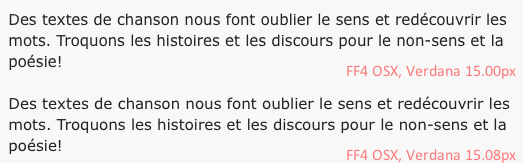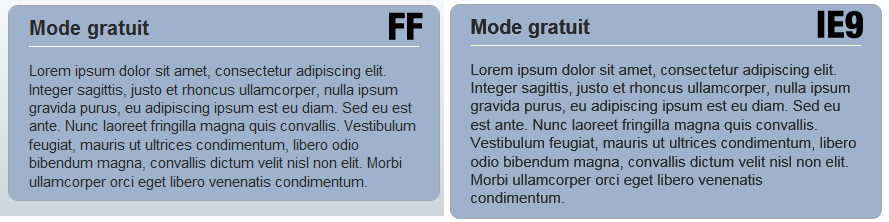
Je suis en train de tester un site sous IE9, et la taille de police est + grosse et + grasse que dans IE8/FF/Safari/Chrome.
Avez-vous remarqué ce problème ?
J'utilise la déclaration suivante pour styler les fontes (issue de yahoo YUI Library) et je déclare ensuite les tailles de polices en pourcentage.
Bonjour,
C'est sans doute dû à l'utilisation de DirectWrite dans IE9 pour le rendu du texte. En gros c'est un rendu du texte plus lissé, qui utilise moins de hinting (adaptation du tracé de la lettre à la grille de pixels) et respecte mieux le dessin original de la lettre. Ça peut donner une impression de texte plus gras.
Pour la taille de texte supérieure, c'est peut-être une question d'arrondi? Quelle est la valeur absolue (computed value) du texte en question?
A quoi correspond la computed value?
Je vais essayer de fixer la taille de la police en pixel et voir ce que ca donne...
Peut-être que l'utilisation des EM serait mieux adapté
A suivre
Quelques résultats avec les styles suivants:
- Sous IE7/IE8/FF/Safari/Chrome : p.pixel et p.pourcent ont la même apparence
- Sous IE9 : p.pourcent est + grand et + gras que p.pixel
Voici le résultat en utilisant les % ( notez également que le dégradé CSS ne passe pas sous IE9 !)
Je veux bien de l'aide, je ne sais pas quoi faire.
Valeur calculée de font-size pour p.pixel: 15px.
Valeur calculée de font-size pour p.pourcent: 15.08px.
Pour une valeur de 15.08px, la plupart des navigateurs vont faire un arrondi à 15px. Mais ce n'est pas systématique, ça dépend du navigateur et du système d'exploitation (et donc des librairies système de rendu des fontes disponibles). Par exemple avec Firefox 4 sur Mac, j'obtiens un rendu différent entre 15.00px et 15.08px:
Tu peux voir les valeurs calculées (computed value) de n'importe quelle propriété CSS pour un élément donné en utilisant Firebug ou un outil équivalent.
Pour des explications sur la notion de valeur calculée, j'ai envie de dire que ça se trouve sans trop de peine sur un moteur de recherche (ou en parcourant la spec CSS 2.1). Smiley smile
Pourquoi donc faudrait-il faire quelque chose?
La différence entre les deux navigateurs ne me choque pas. En passant, tu as testé avec Firefox 4? Firefox aussi a apporté des changements à son rendu des fontes, donc tu peux avoir ce type de différence entre Firefox 3.6 et FF4.
La solution consiste donc à apprendre le lâcher-prise, et à ne rien faire. Smiley smile
Pour les typos, en passant à 115%, je suis à 14.95px en valeur calculée, et le rendu est le même sous FF et IE9 (soit 15px)
Apparement, IE9 n'arrondi pas à l'entier inférieur..
En tout ca, je trouve le nouveau rendu des polices sous IE9 à ch*er, on dirait de la grosse bouillie !
Question d'habitude. Vraiment.